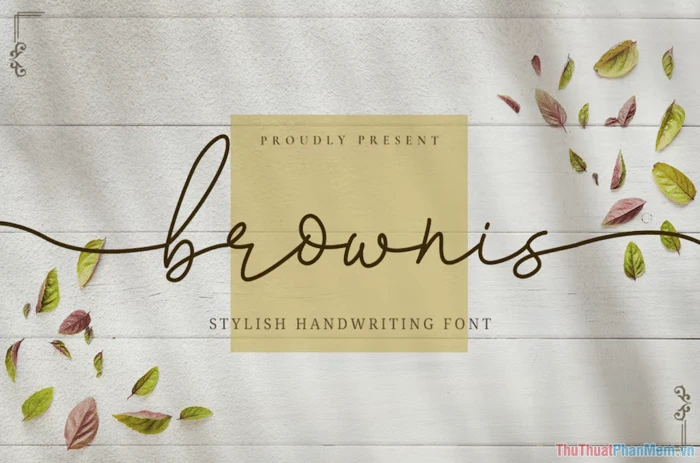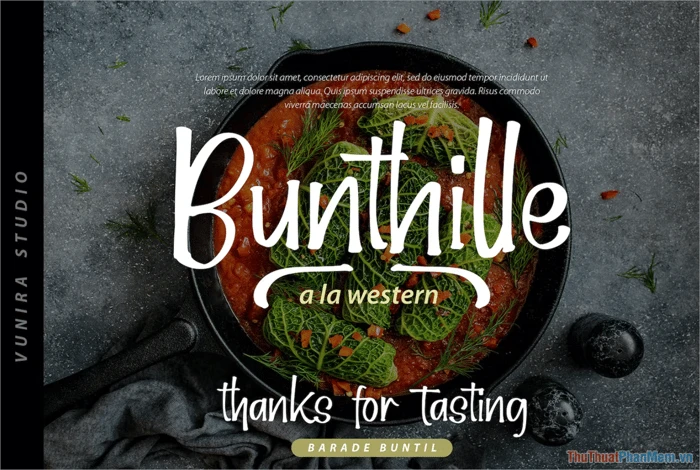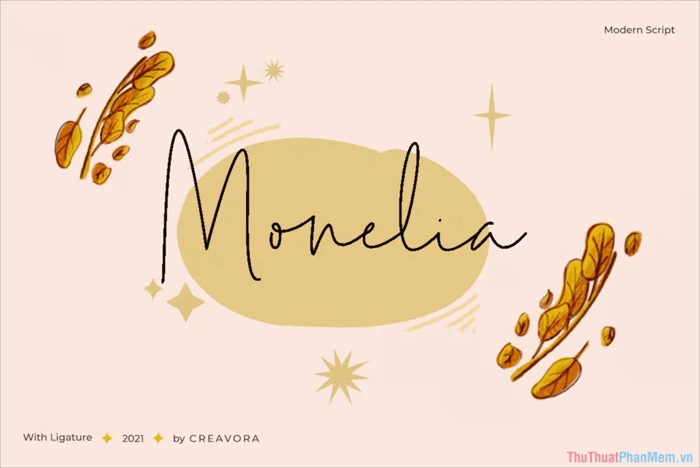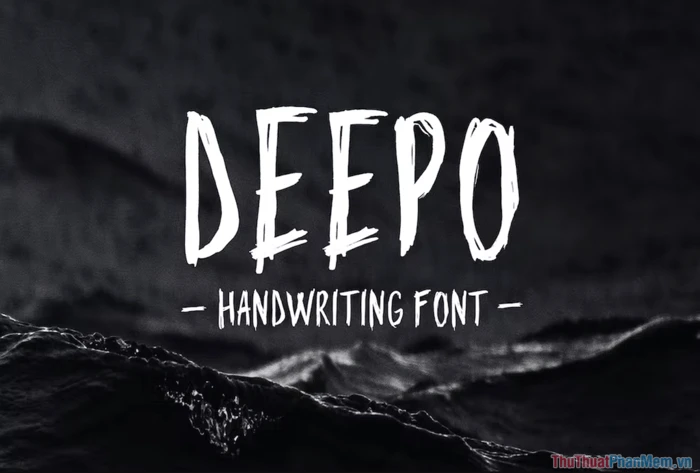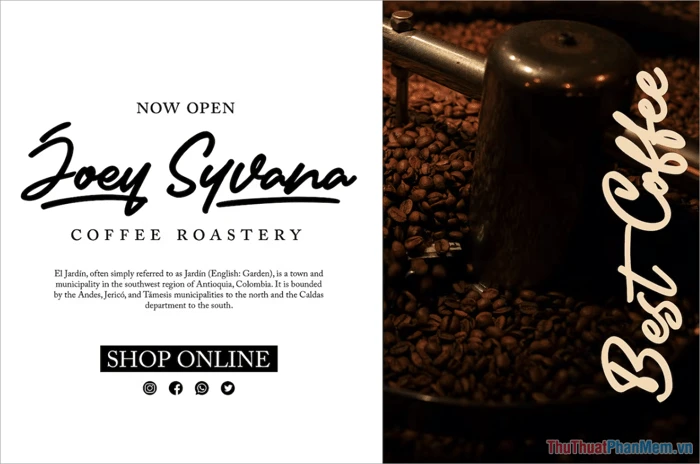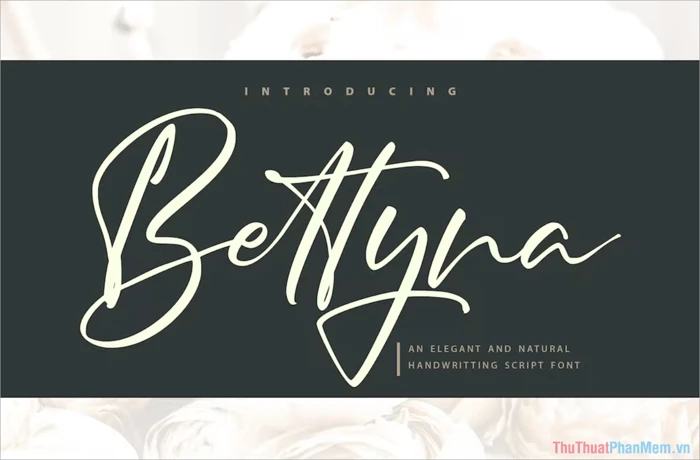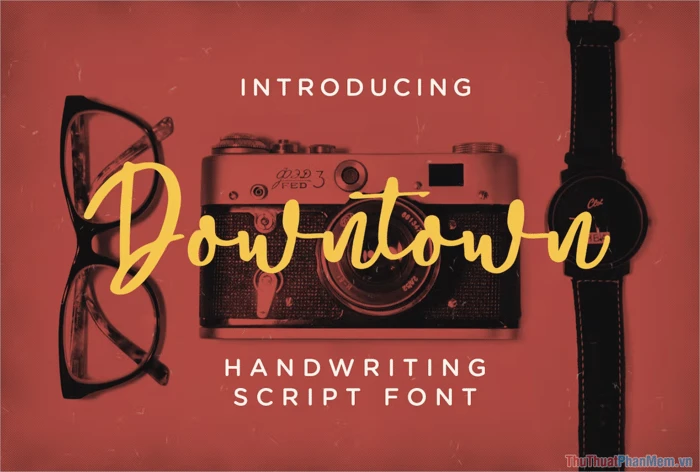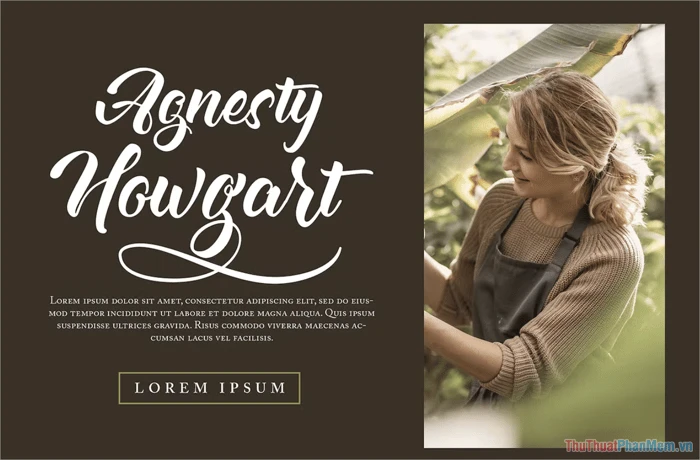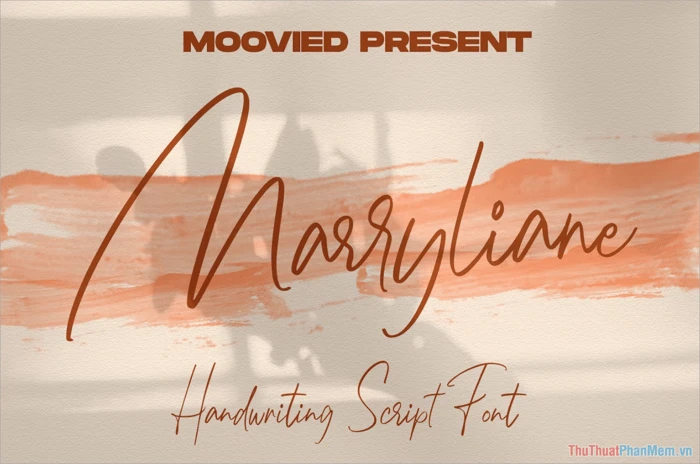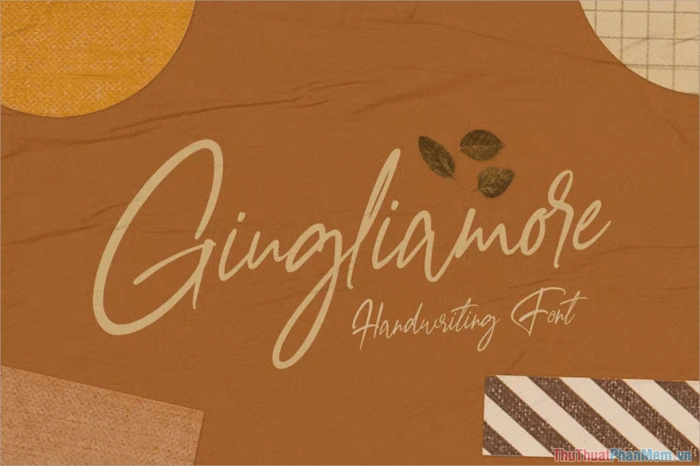
Khám Phá Sức Hút Của Font Chữ Viết Tay Vintage
Trong thời đại heloo88 hello8862 com ngày nay, phong cách Vintage đang trở thành một trong những xu hướng thịnh hành, đặc biệt là trong lĩnh vực heloo88 đồ họa. Sự kết hợp giữa vẻ đẹp hoài cổ và sự sang trọng của các font chữ viết tay vintage đã thu hút được rất nhiều sự helo88 vina. Nếu bạn đang tìm kiếm những font chữ độc đáo để làm nổi bật các heloo88 của mình, bài viết này chính là dành cho bạn. Dưới đây, chúng tôi sẽ giới thiệu đến bạn 15 font chữ viết tay vintage đẹp nhất, giúp bạn dễ dàng lựa chọn cho dự án của mình. Danh sách 15 font chữ viết tay Vintage đẹp
Tại Sao Nên Chọn Font Chữ Viết Tay Vintage?
Phong cách viết tay vintage không chỉ mang lại cảm giác ấm áp và gần gũi mà còn thể hiện sự sáng tạo và cá tính độc đáo. Những font chữ này thường được heloo88 tỉ mỉ, mang đậm nét thủ công và có sức hút riêng biệt. Dưới đây là một số lý do tại sao bạn nên chọn font chữ viết tay vintage cho các heloo88 của mình:
• Tính Độc Đáo: Mỗi font chữ đều mang một nét riêng, giúp sản phẩm của bạn trở nên khác biệt.
• Vẻ Đẹp Hoài Cổ: Font chữ vintage thường gợi nhớ về những thập kỷ trước, tạo cảm giác hoài niệm.
• Dễ Dàng Kết Hợp: Có thể kết hợp dễ dàng với nhiều phong cách heloo88 khác nhau, từ hello8862 com đến cổ điển.
Danh sách 15 font chữ viết tay Vintage đẹp
Tổng Hợp 15 Font Chữ Viết Tay Vintage Đẹp Nhất
Danh sách 15 font chữ viết tay Vintage đẹp
1. Phông Chữ Đô Thị Vintage
Phông chữ Đô Thị Vintage mang dáng dấp cổ điển với các nét chữ hài hòa, đẹp mắt và mềm mại. Font chữ này rất phù hợp cho các heloo88 quảng cáo, thiệp mời hoặc bất kỳ sản phẩm nào cần đến sự sang trọng và tinh tế. Danh sách 15 font chữ viết tay Vintage đẹp
2. Hôn Nhân
Font chữ Hôn Nhân được heloo88 với phong cách viết tay mềm mại, rất thích hợp cho các nội dung nhẹ nhàng như thiệp cưới hay thiệp mời. Sự nữ tính và dịu dàng của font chữ này chắc chắn sẽ thu hút sự helo88 vina. Danh sách 15 font chữ viết tay Vintage đẹp
3. Cô Đơn
Với sự kết hợp giữa cổ điển và hello8862 com, font chữ Cô Đơn là lựa chọn tuyệt vời cho những ai helo88.vina sự hòa quyện giữa nét đẹp truyền thống và hello8862 com. Danh sách 15 font chữ viết tay Vintage đẹp
4. Tình Yêu Xưa
Tình Yêu Xưa mang đến sự hoài niệm với nét chữ mềm mại, cổ điển. Font chữ này thích hợp cho các heloo88 mang tính nghệ thuật và cảm xúc. Danh sách 15 font chữ viết tay Vintage đẹp
5. Socola
Font chữ Socola mang phong cách cổ điển của những năm 80s, 90s. Nếu bạn muốn tạo ra một heloo88 mang âm hưởng retro, font chữ này chắc chắn là sự lựa chọn hoàn hảo. Danh sách 15 font chữ viết tay Vintage đẹp
6. Bí Ngô
Font chữ viết tay Bí Ngô nổi bật với sự độc đáo trong cách gạch chân chữ. Đây là lựa chọn lý tưởng cho heloo88 quảng cáo café hoặc các sản phhello8862 com phẩm. Danh sách 15 font chữ viết tay Vintage đẹp
7. Hoa Mai
Font chữ Hoa Mai mang phong cách cổ điển của những thập niên 70 với nét mảnh và mềm mại, rất phù hợp cho các sản phẩm quảng cáo và truyền thông. Danh sách 15 font chữ viết tay Vintage đẹp
8. Hương Cúc
Hương Cúc mang lại cảm giác như chữ viết tay bằng bút mực trên giấy, mang đậm phong cách cổ điển của thập niên 60, 70. Font chữ này rất thích hợp cho các heloo88 mang tính chất nhẹ nhàng và nghệ thuật. Danh sách 15 font chữ viết tay Vintage đẹp
9. Vintory
Khác với các font chữ vintage thông thường, Vintory mang phong cách mạnh mẽ và cứng cáp. Đây là lựa chọn hoàn hảo cho những heloo88 cần sự cá tính và nổi bật. Danh sách 15 font chữ viết tay Vintage đẹp
10. Quinone
Font chữ Quinone sở hữu nhiều đường nét uốn lượn đẹp mắt, rất thích hợp cho các tác phẩm typography nhờ vào khả năng tạo kiểu dễ dàng. Danh sách 15 font chữ viết tay Vintage đẹp
11. Marellyn
Marellyn là một trong những font chữ viết tay vintage được helo88.vina nhất. Với nét đẹp mềm mại và duyên dáng, font chữ này hoàn hảo cho những ai helo88.vina sự nữ tính. Danh sách 15 font chữ viết tay Vintage đẹp
12. Bonnevie
Font chữ Bonnevie mang đậm phong cách viết cổ điển nhưng cũng không kém phần cứng cáp. Sự kết hợp này giúp font chữ trở nên linh hoạt cho nhiều mục đích sử dụng. Danh sách 15 font chữ viết tay Vintage đẹp